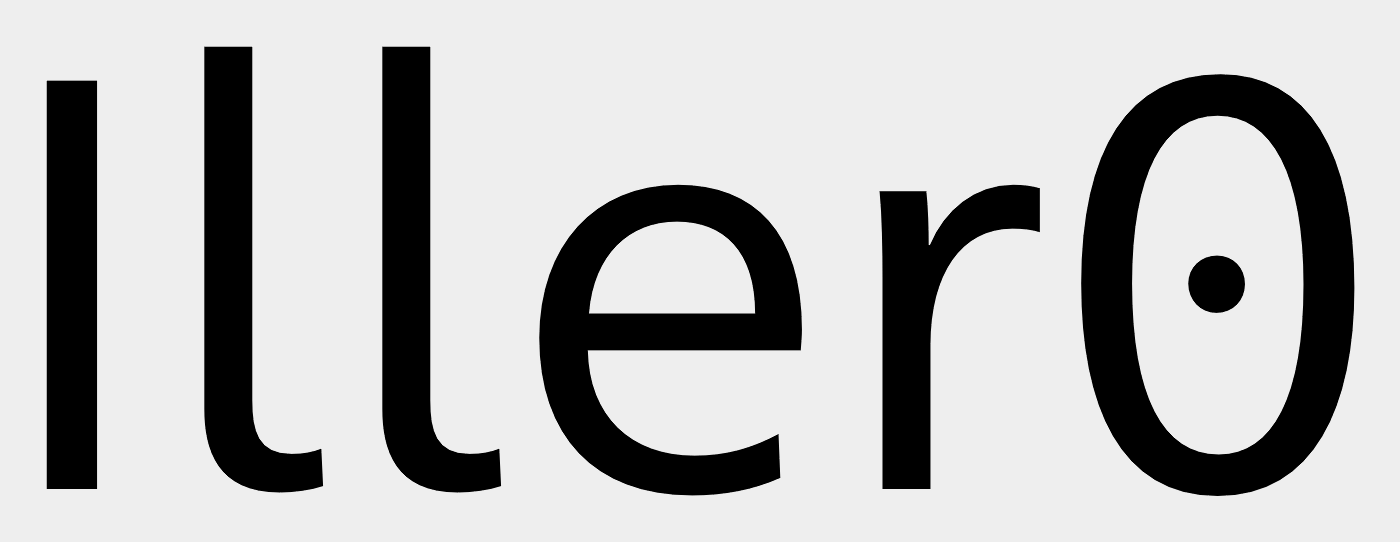
Schriften für technische Dokumente
suche ein paar Fonts, die für technische Dokumente (Fließtext) geeignet sind. Also eindeutige Zeichenunterscheidungen von Groß- und Kleinbuchstaben sowie Ziffern. In Arial liest sich großes I wie kleines l etc.
Unser Marketing möchte die Segoe verwenden um die Zahl verschiedener Fonts zu verringern. Wäre die (zufälligerweise) auch für TD geeignet? :aschehaupt:
Segoe ist auch nicht gut für eindeutige Unterscheidung, konnte ich eben im Illu testen.
Sollte ich gefragt werden, nenne ich die Neue Frutiger mal als Vorschlag. Danke! :-)
:-? Nullen waren hier aber nicht ausschlaggebend – müsste also noch geprüft werden – und es braucht teilweise Opentype-Einstellungen um die gewünschte Unterscheidung herzustellen. :roll:
Muss es denn überhaupt eine Serifenlose sein?
Danke. Dass wir umstellen ist unwahrscheinlich, da der Aufwand nicht zu stemmen wäre ...
Hmm.. im Unternehmen werden nur serifenlose verwendet, soweit ich das überblicken kann ….